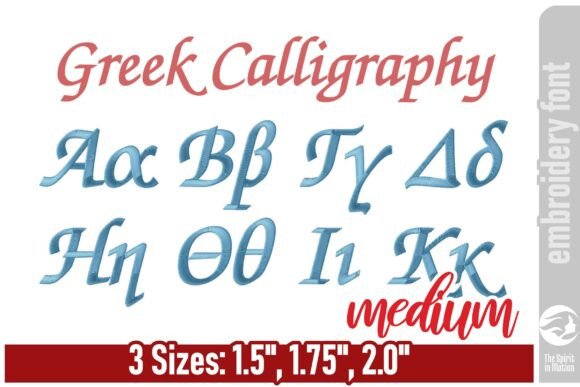
Greek Calligraphy Embroidery Font - M
Поиск подходящих элементов дизайна может быть сложным, но Greek Calligraphy Embroidery Font - M предлагает исключительную коллекцию, которая мгновенно улучшит вашу работу.
Создаете ли вы продукты POD (печать по требованию), свадебные приглашения или графику для социальных сетей, Greek Calligraphy Embroidery Font - M станет идеальным выбором.